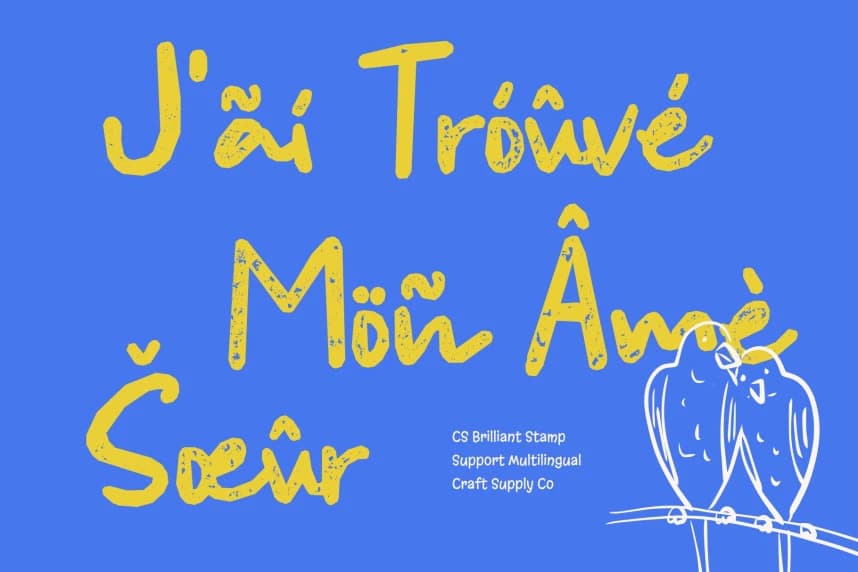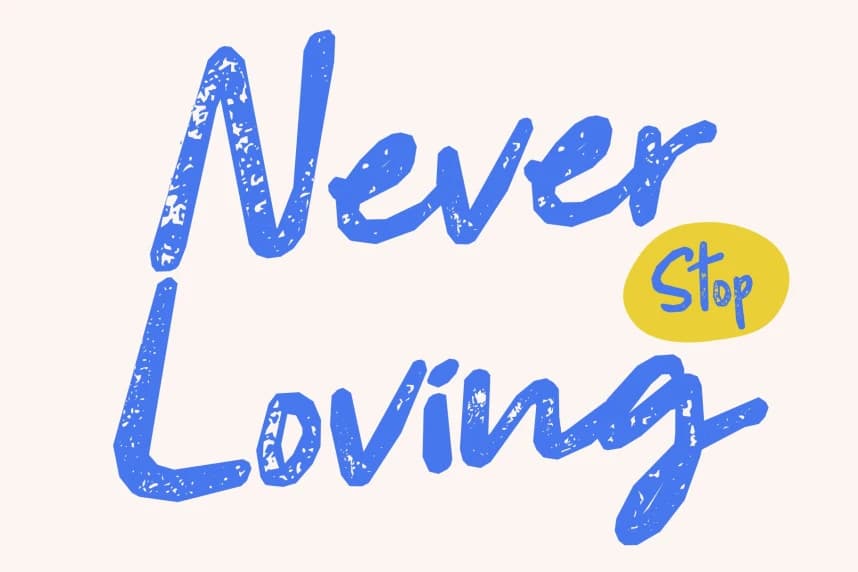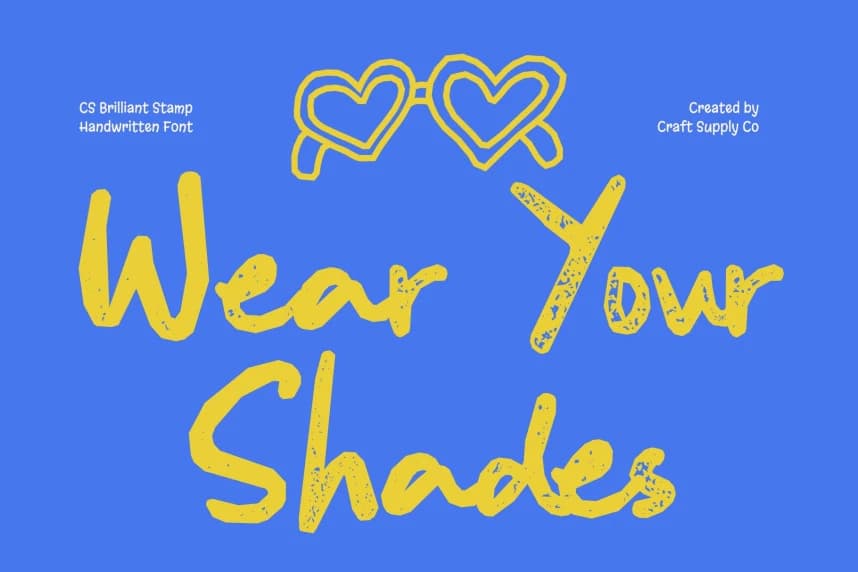
CS Brilliant Stamp Font
CS Brilliant Stamp Font – Dokulu Çekiciliğe Sahip El Yazısı Sıcaklığı; Doğal Bir Hissiyat Veren Yumuşak El Yazısı Betik Fontu. Bu, doğal kalem darbelerinin güzelliğini temiz bir görünüm ile yakalamak üzere tasarlanmış bir el yazısı betik fontudur.
CS Brilliant Stamp Font – Doğal dokulu çekicilik ile el yazısı sıcaklığı; Doğal Hissiyatlı Yumuşak El Yazısı Script. Bu, doğal kalem darbelerinin güzelliğini temiz bir görünümle yakalamak için tasarlanmış bir el yazısı script fontudur.
CS Brilliant Stamp